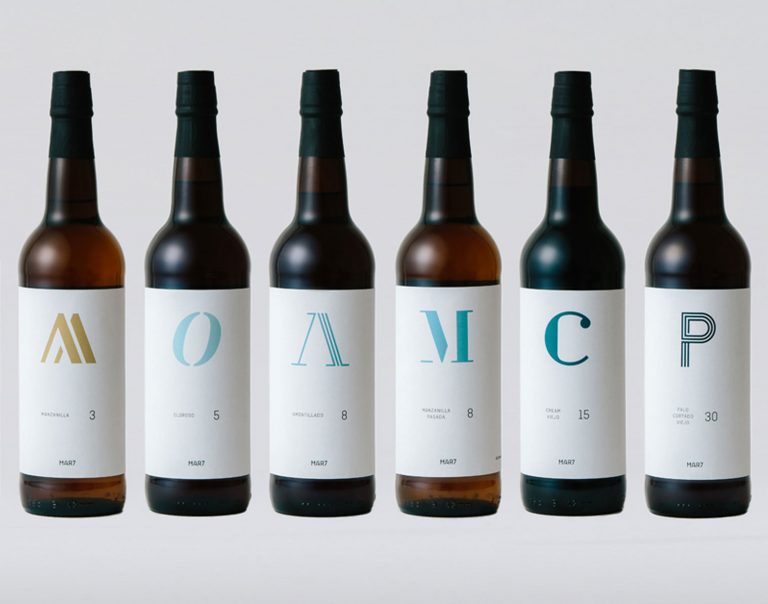
Fernando Suárez está al frente del estudio de diseño gráfico Habermas, bautizado con ese nombre en honor al filósofo, sociólogo y teórico de la comunicación Jürgen Habermas, cuya primera sede estaba situada en la sevillana calle del Porvenir. Mimbres intelectuales y buenos augurios para un estudio que a día de hoy atesora un más que bien merecido prestigio.
En Habermas se tocan todos los palos del diseño (gráfico, web, editorial, etc.), pero donde realmente destaca es en la vertiente de diseño de packaging, disciplina donde han cosechado numerosos reconocimientos y galardones, entre los que sobresalen nada menos que cinco premios Laus.
Después de más de quince años de trayectoria profesional, Fernando Suárez se encuentra en plena madurez profesional y creativa, y por ello hemos querido charlar con él para que nos devele los entresijos de un buen packaging y su inevitable relación con la tipografía.
Rayitas Azules: Uno de los grandes retos a la hora de diseñar, ya sea packaging, señalética o cualquier otro elemento informativo es, sin duda, la legibilidad, además de evitar la saturación de información, es decir, ser siempre claro y preciso. ¿Qué directrices soléis seguir a la hora de manejar tipografía de pequeño tamaño? ¿Os decantáis por los iconos de ayuda o preferís manejar solo texto? ¿Tenéis al respecto algún consejo o algún hábito especial?
Fernando Suárez: Las directrices para seleccionar unas fuentes u otras varía en función de las limitaciones de espacio. Cuando hay poco espacio y mucha información utilizamos fuentes que a pequeña escala sean legibles, además de compensar con recursos visuales como la iconografía. Esta nos permite compensar o reforzar la información.
RA: ¿Cómo soléis tratar la jerarquía o el contraste de las tipografías de los descriptores en relación a la de la marca?
FS: En estos casos intentamos que el descriptor conviva perfectamente con la marca. Que se integre bien en la zona de confort. Otras veces el descriptor está fuera de esa zona de confort de la marca y lo acompaña en distintas ubicaciones.
RA: ¿Nos podrías explicar un poco de qué manera influye el material en que se realizará el packaging en la elección de la tipografía? ¿Cuáles crees que son los materiales o el sistema de impresión que más distorsionan una tipografía? ¿Soléis realizar muchas pruebas de impresión?
FS: El material influye bastante. Pero, para nosotros, el papel no nos condiciona la selección de la tipografía. Seleccionamos la tipografía en base a otros criterios.
Los materiales que mas distorsionan la tipografía son los plásticos junto con la impresión directa en vidrio. Cuando tenemos que imprimir directamente en estos materiales hay que cambiar el chip ya que tenemos que adaptarnos bastante a las limitaciones que nos imponen estos materiales.
Hacemos varias pruebas en papel y la ultima prueba nos la hace el impresor.
RA: ¿Crees que existe una tipo infalible, esa que siempre, siempre funciona, independientemente del producto?
FS: Sí, sí. Existen los clásicos, esos son un valor seguro.
RA: ¿Cuáles son esos clásicos para ti?
FS: Bodoni, Avenir, Helvética, Frutiger, Gil Sans y Garamond.
RA: En cuanto al kerning y el tracking, ¿sueles «tocar» estos parámetros a la hora de crear pastillas de texto para los envases? ¿Algún «truco» especial?
FS: Sí que tocamos estos parámetros en función del espacio que tengamos. Los ajustamos porque muchas veces a pequeña escala la legibilidad se pierde, y para aumentarla, no tenemos mas remedio que tocar el kerning y el tracking.
RA: ¿Usáis un elevado número de fuentes diferentes a la hora de diseñar o creéis que con un par de tipos es suficiente? ¿Tenéis alguna debilidad tipográfica?
FS: No. Usamos tres como mucho, dependiendo del tipo de trabajo. Si es un trabajo de packaging solemos usar dos o tres. Si es un trabajo editorial, unas cuatro y para un proyecto de branding, dos.
RA: Decís al respecto del diseño de la línea de etiquetas para Bodega de Vinos de Sanlúcar de Barrameda, Mar7, (proyecto que os valió un Laus de bronce en 2016) que «el objetivo de la imagen de la serie es innovar, diferenciando al producto dentro de un sector de una zona vinícola muy tradicional como es el Marco de Jerez, donde la mayoría de los vinos siguen criterios estéticos comunes». ¿Podemos decir que otorgar a la tipografía un papel claramente preponderante es la principal es innovación?
FS: No. En este caso la innovación ha sido romper con los códigos visuales característicos de este sector concreto. Etiquetas muy recargadas, mucha mancha, mucho stamping, y maquetación irregular. Nosotros hemos ordenado todo esto y lo hemos depurado, jerarquizando los elementos más importantes y dandole valor a ciertos aspectos del producto como la vejez. En este caso la tipografía la hemos utilizado como recurso gráfico para darle visibilidad a cada uno de los tipos de vino.
RA: ¿Qué pensáis del uso de la tipografías monoespaciadas en packaging? ¿Las habéis usado alguna vez?
FS: No nos gustan mucho, pero si el envase o el producto nos lo pide, lo hacemos sin problemas.
RA: ¿Cuál es tu «top cinco» tipográfico para packaging?
FS: Avenir: Es muy legible y la usamos tanto como tipo principal como secundaria
Periódico: Aporta solvencia y elegancia al envase. La usamos como tipografía principal.
Din: Es muy buena como tipografía secundaria, a pequeñas escalas funciona muy bien.
Aleo: De las tipografias con serifa es de las que más nos gusta para utilizar en packaging es muy legible y actual.
Helvetica: funciona bien como principal y como secundaria. Es muy legible en todos los formatos y tipos de papel.
RA: Y para terminar, queremos hacerte una pregunta que no se centra solo en la tipografía, sino que apunta más a la intención o finalidad del diseño en general: ¿un envase tiene que convencer o seducir?
FS: A ver, esta pregunta es muy buena y compleja para contestarla en una frase. Yo personalmente, pienso que depende que producto y a quien vaya dirigido, debería despertar emociones o no.
Es decir, hay envases que por el tipo de producto es suficiente que convenzan al comprador (son más racionales), y hay envases que, por el tipo de producto, deberían seducir al comprador (despertar alguna emoción).